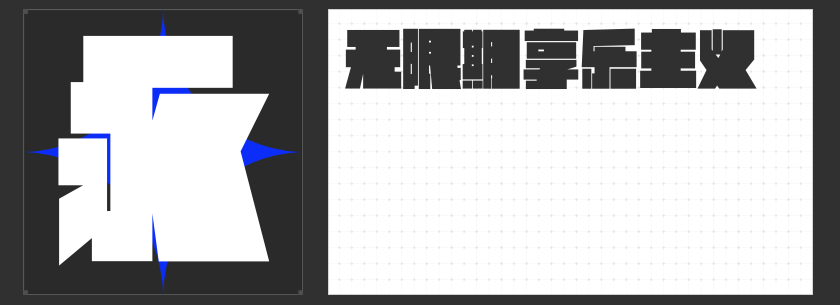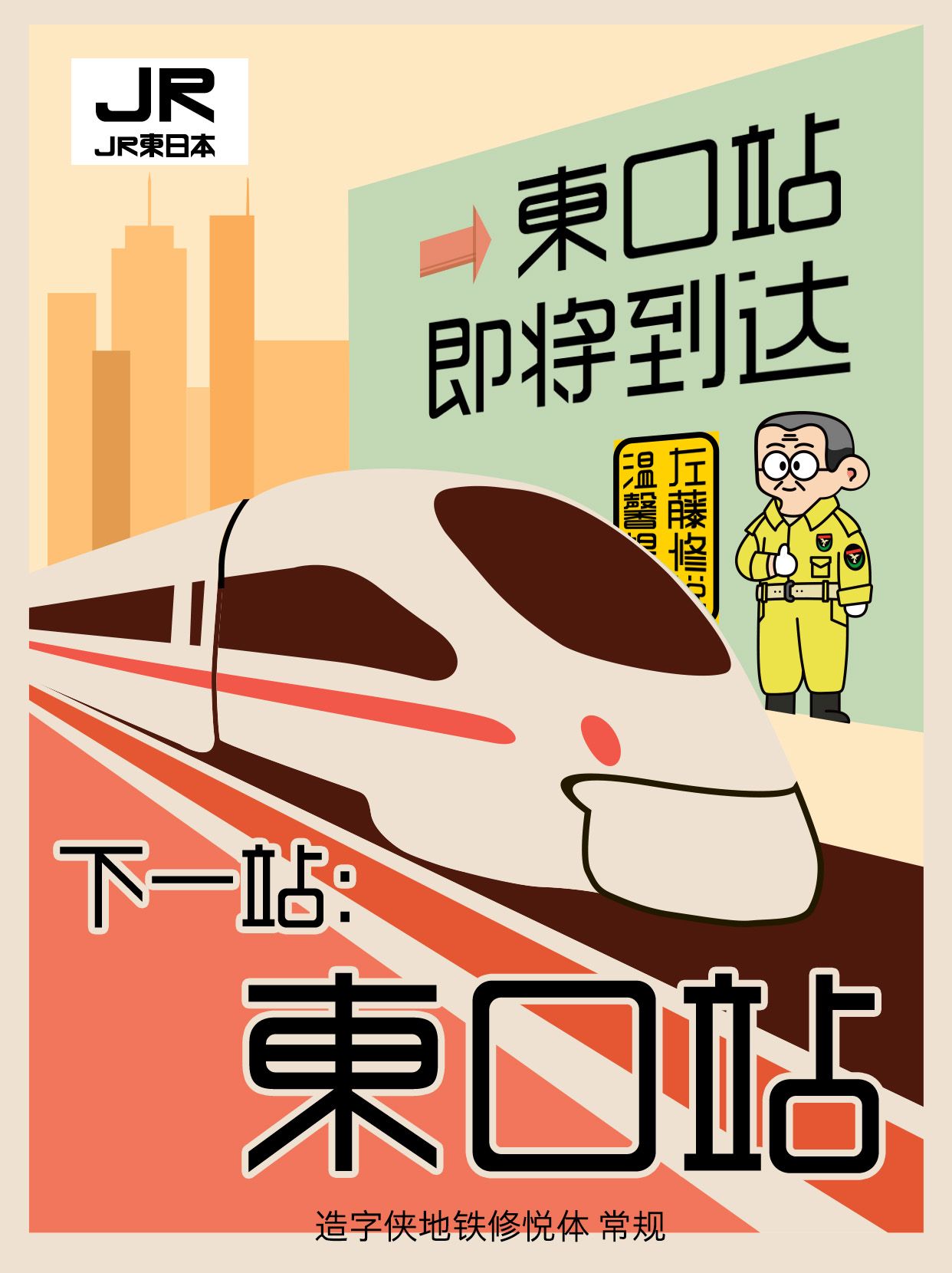
四款创意字体推荐:打破常规,为设计注入先锋美学
在视觉表达日益追求个性化的当下,字体的选择早已超越“可读性”的单一维度,成为传递品牌态度、塑造场景氛围的关键。今天推荐四款风格鲜明的创意字体,它们以独特的造型逻辑和设计哲学,为品牌设计、文化传播、空间导视等领域注入先锋力量。
1. 造字侠地铁修悦体 常规
这款字体灵感源自日本地铁工作人员佐藤修悦的胶带指路艺术。以胶带拼贴为视觉语言,将工业材料的粗粝感与人文关怀结合,笔画边缘保留胶带粘贴的毛边质感,字形方正却不失温度。它适合城市公共空间导视、公益广告或文化展陈设计,让信息传递兼具实用性与情感共鸣,仿佛每一笔都在讲述“为他人点亮方向”的故事。
2. 励字暴风简 超级黑
作为一款现代创意黑体,励字暴风简以“梯形”为基因密码,打破传统黑体的均衡感。横竖笔画呈梯形分布,撇捺点划融入更多几何切割,笔画粗细的不均等处理带来强烈的视觉张力。其硬朗风格适用于科技品牌、工业设计或潮流文化领域,既能传递力量感,又暗含打破常规的叛逆精神,让标题文字成为视觉焦点。
3. 励字宽边黑简 超级黑
这款字体通过“右粗左细”的笔画对比,构建出极具张力的空间感。横平竖直的骨架中,右侧加粗的笔画如雕塑般突出,左侧减细的线条则形成呼吸感,形成动态平衡。其规整的方块结构与强烈的粗细反差,适合用于电影海报、奢侈品包装或建筑空间标识,在秩序中制造冲突,在对比中彰显高级感。
4. 高手字斋哥特体Pro
区别于传统哥特体的狭长结构,这款字体以“等宽方块”重塑哥特基因。笔画如刀锋般锐利,横竖撇捺皆有棱角,却通过光洁平滑的曲线平衡了攻击性,形成“刚柔并济”的视觉体验。无论是品牌LOGO、书籍封面还是数字媒体标题,它都能以高辨识度跳出背景,同时以文化基因的深度统一性,适配东方美学与现代设计的融合场景。
字体是设计的无声语言,更是品牌态度的视觉宣言。这四款字体以突破性的造型逻辑,将功能性与艺术性熔于一炉,为创意表达提供无限可能。无论是追求人文温度、工业力量,还是锋利觉醒,它们都能成为你设计中的“点睛之笔”。